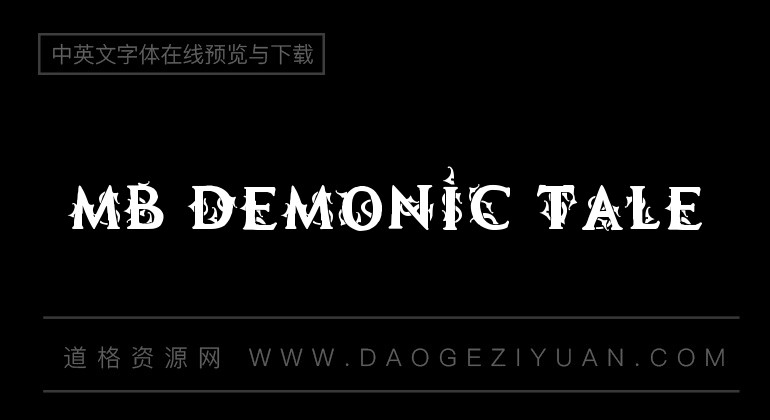
MB Demonic Tale
MB Demonic Tale是一种非常独特并具有特殊效果的字体,它的设计灵感来自于魔鬼和黑暗的世界。 该字体的字形非常奇特,每个字母都被设计成了一种独特的魔鬼符号。其整体风格非常神秘、黑暗和有力,为设计师在制作一些恐怖、黑暗和幽灵主题的作品时提供了很好的选择。 MB Demonic Tale字体适用于海报、书籍、漫画、电影、电视节目、游戏和各种商业项目等等。另外,该字体还支持多种语言,包括英语、西班牙语、法语、德语、荷兰语、意大利语、葡萄牙语等。 总之,如果你需要一种神秘、黑暗和有力的字体来增强你的设计作品的视觉效果,MB Demonic Tale是一个不错的选择。
MB Demonic Tale是一款非常不错的手写艺术字体,具有很好的视觉感,适合于文化类的宣传设计、商业类品牌的广告和产品包装设计以及个性化文字排版等较多场景。